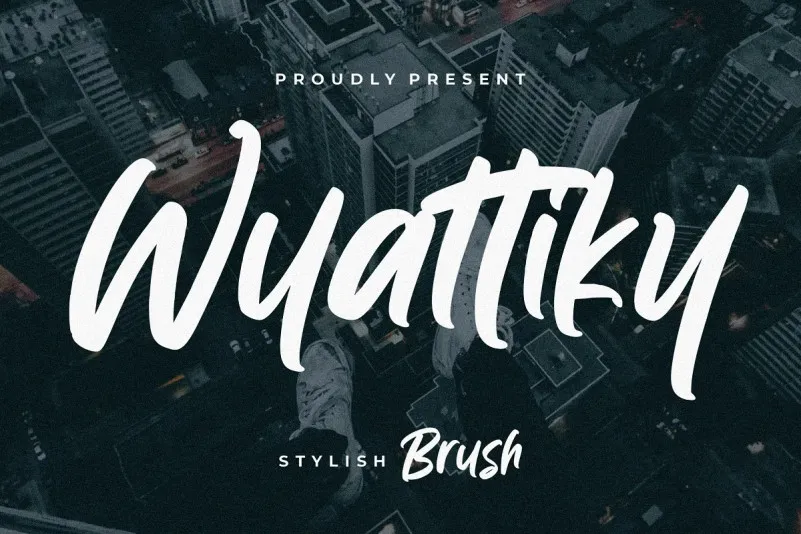
Wyattiky Font – Download Grátis
Wyattiky Font é uma elegante fonte de script criada pelo Creatype Studio com um estilo casual e fashionista. Desenvolvida para oferecer a personalidade única do traço natural das mãos, essa fonte atende perfeitamente aos projetos variados como branding, logomarca, designs de casamento, posts nas redes sociais, anúncios, embalagens de produto, design de produtos, etiquetas, fotografia, marca impressa e até mesmo para criação de cópias digitais. Seja qual for o projeto que precisa de uma pitada de escrita natural, a Wyattiky Font se destaca como uma opção inteligente. Engajante, versátil e extremamente adaptável, ela tornará seu próximo design um sucesso.